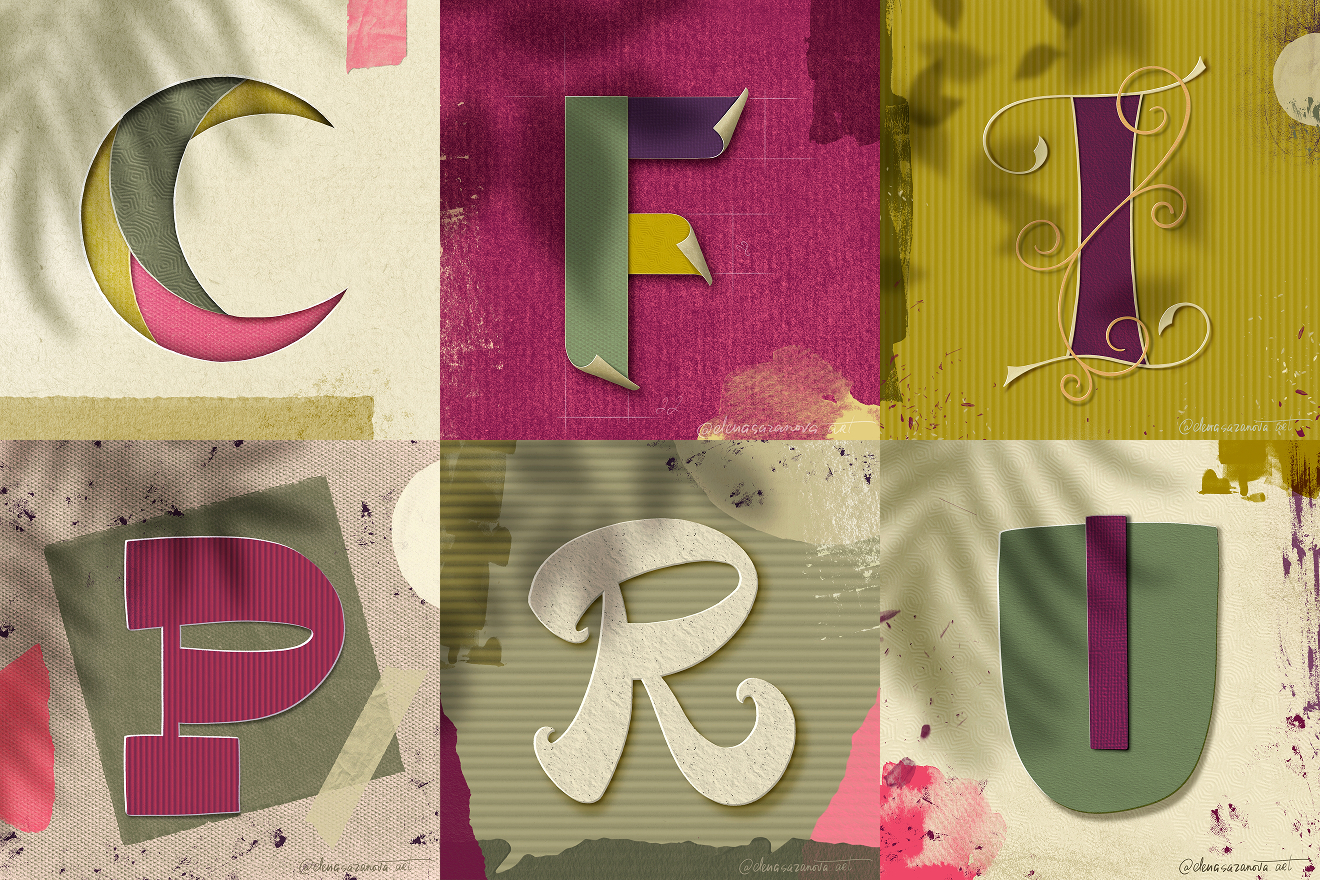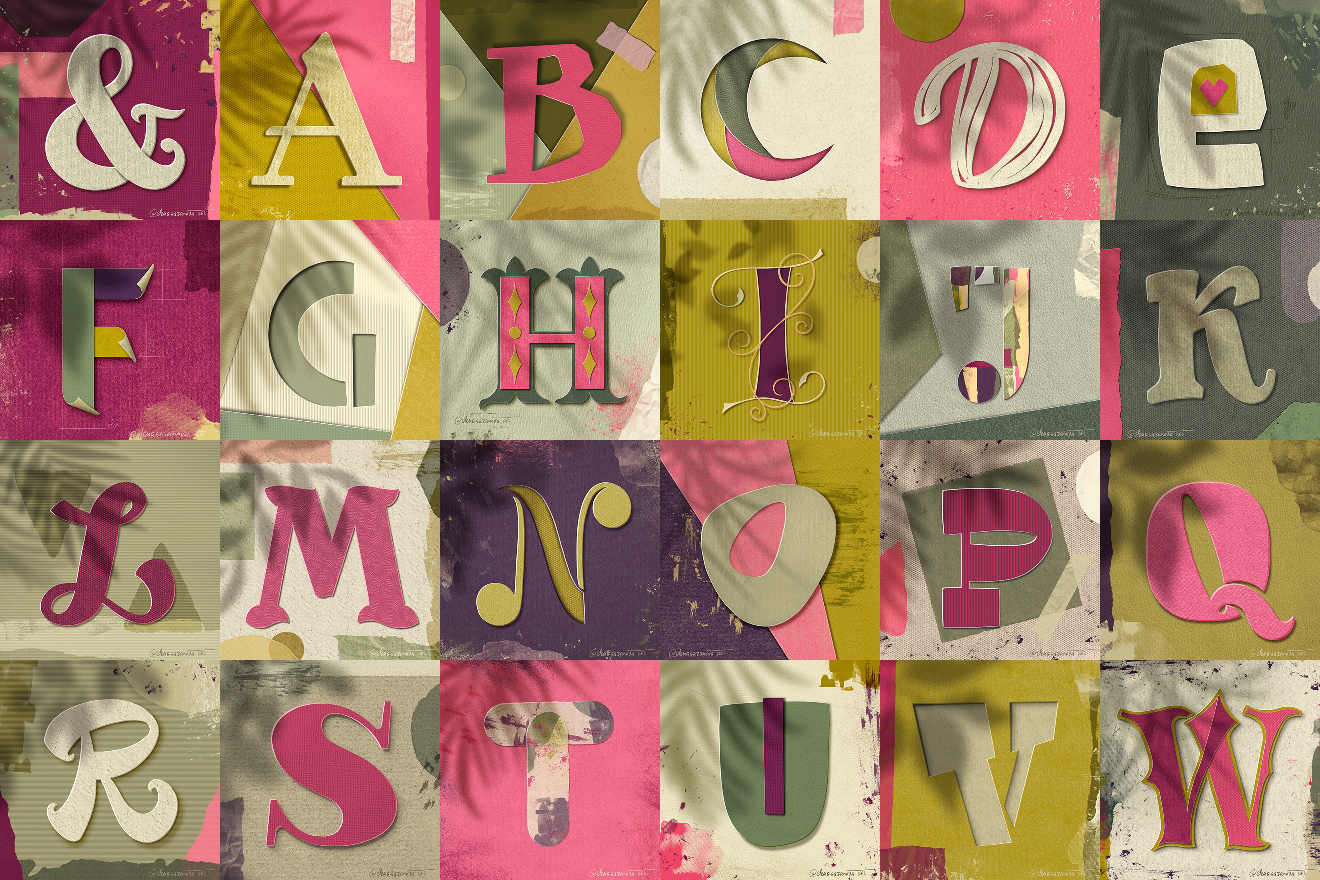
Алфавит для челленджа 36daysoftype
Алфавит с буквами в стиле бумажной аппликации был создан в рамках челленджа 36daysoftype в Procreate на iPad в 2021 году.